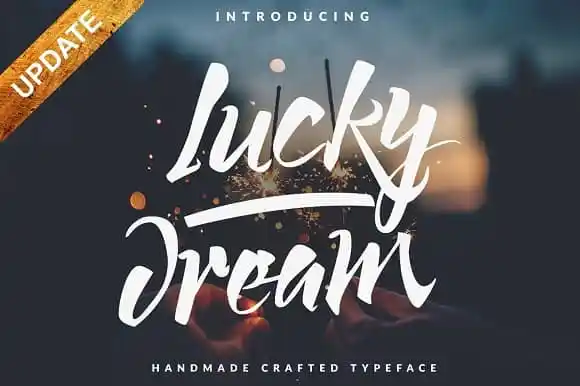
Lucky Dream Script Font – Download Grátis
Descubra Lucky Dream Script Font, uma elegante tipografia criada pelo estúdio Putra Khan Studio. Esta fonte brush é perfeita para projetos modernos e vivos, ideal tanto para títulos quanto para detalhes menores como logotipos, selos ou até cartões de casamento. Com um estilo único e artesanal, Lucky Dream se adapta a várias necessidades gráficas, tornando-a uma opção versátil e poderosa para seu próximo projeto de design. Se você está procurando por algo autêntico e criativo, esta fonte será certamente sua perfeita escolha. É um presente do universo da design gratuitamente disponível na plataforma Creativemarket, oferecendo a todos uma maneira incrível de adicionar personalidade e estilo à suas criações digitais.